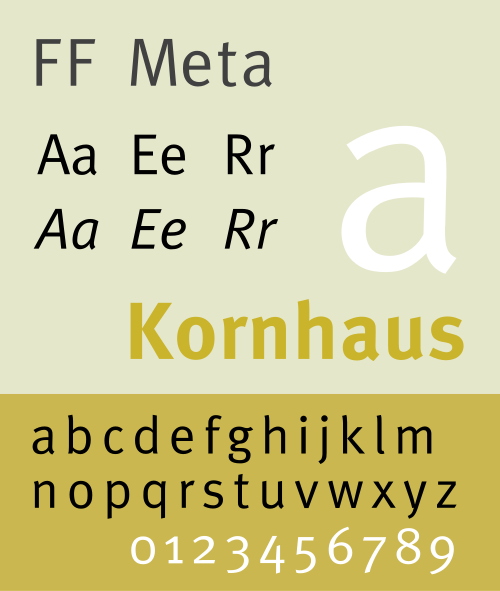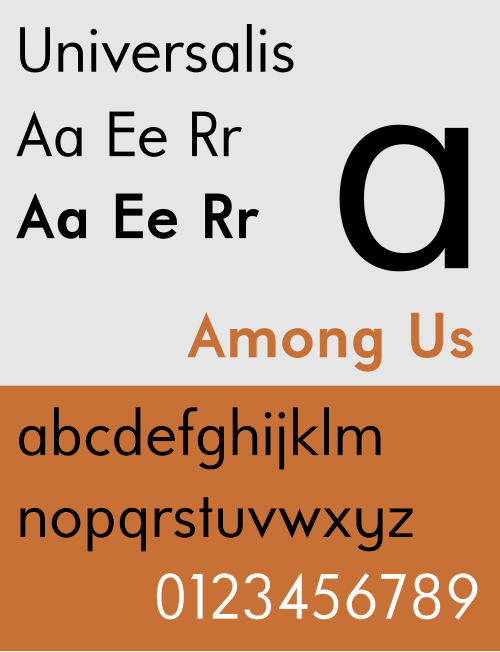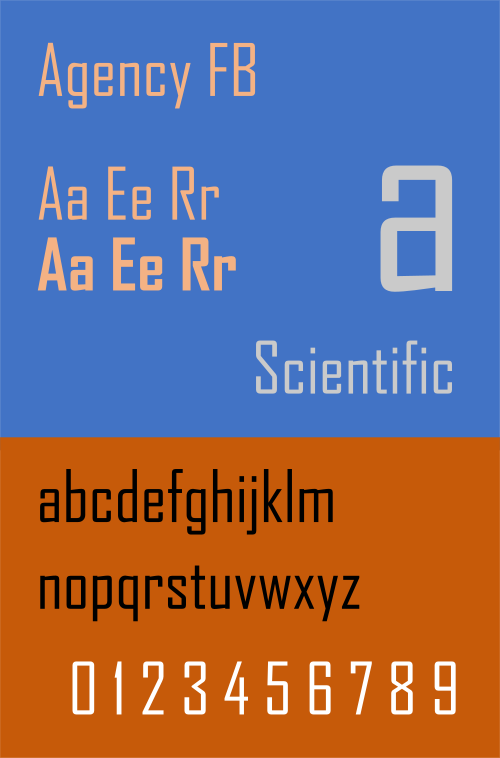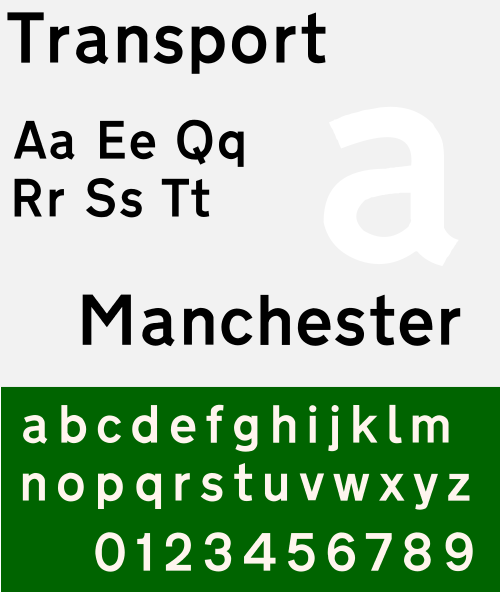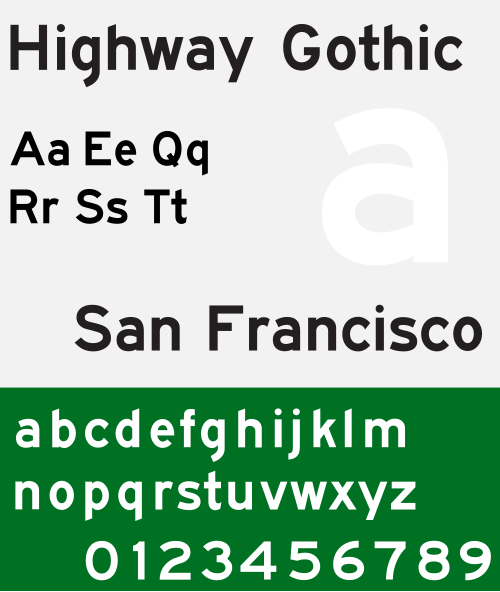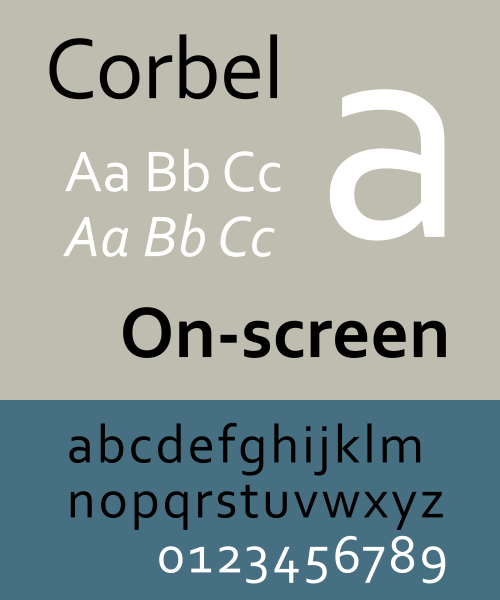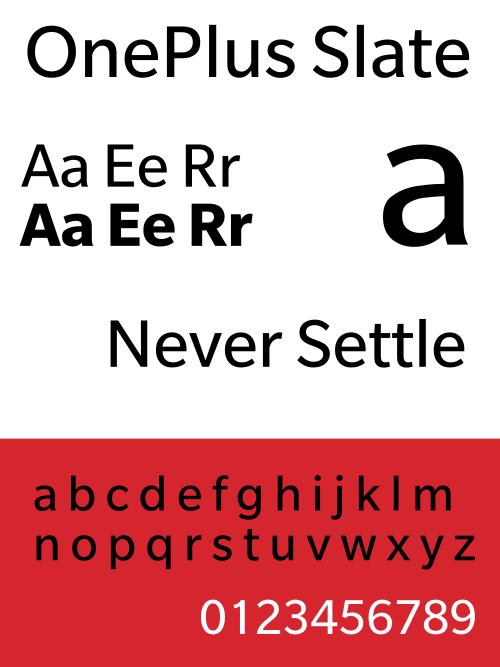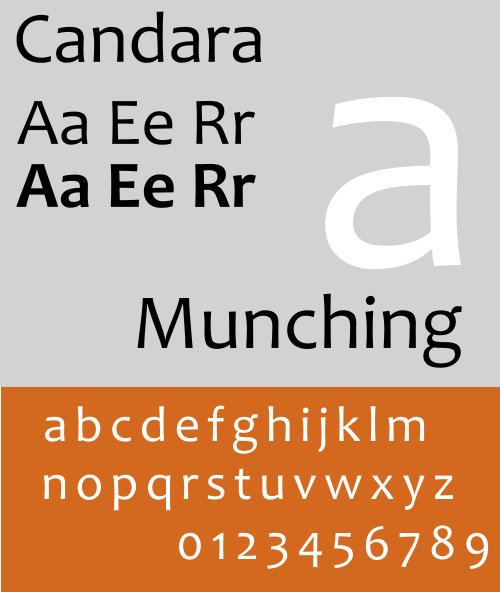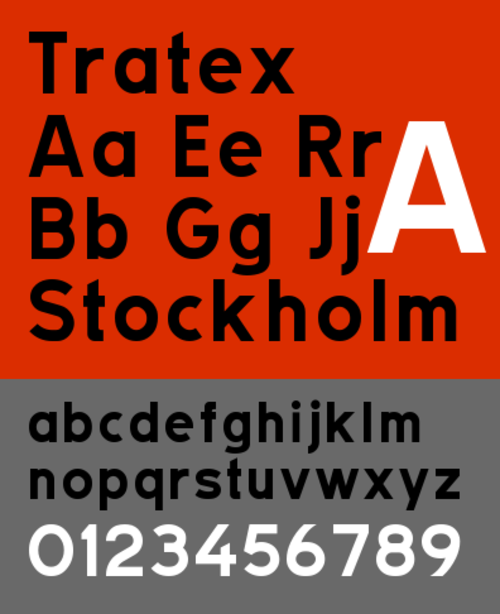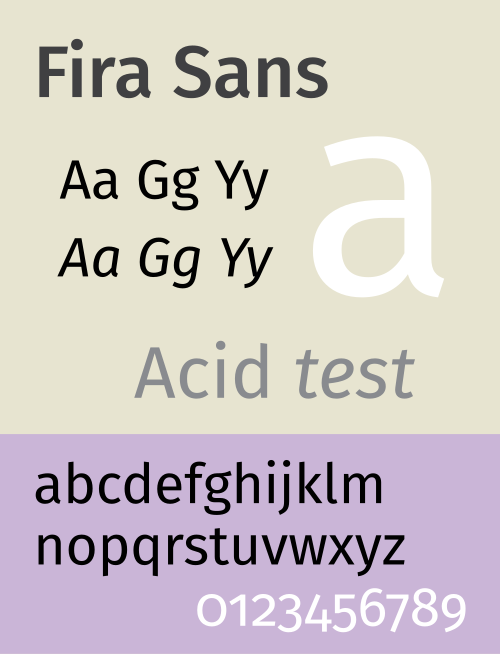
قائمة بأنواع الخطوط غير المزخرفة (sans serif)
تتضمن هذه القائمة تفاصيل عن أنواع الخطوط غير المزخرفة ( sans-serif) القياسية المستخدمة في الطباعة والتنضيد الكلاسيكي .
| مصممو وكالة فيسبوك : كالي هوبر وموريس فولر بنتون، الفئة: هندسي | |||
| Akzidenz-Grotesk المصمم: Günter Gerhard Lange الفئة: Grotesque | |||
| مصمم السعة : كريستيان شوارتز، الفئة: إنسانية | غير متوفر | |
| مصمم أندالي سانس : ستيف ماتيسون، النوع: إنساني | غير متوفر | |
| زيتون عتيق، المصمم: روجر إكسكوفون، التصنيف: إنساني | |||
| أبتوس، المصمم: ستيف ماتيسون، النوع: نيو-غروتيسك | غير متوفر | |
| مصمم الأرشيف : هيكتور جاتي، فئة النوع Omnibus: Grotesque | |||
| مصممو خط أريال : روبن نيكولاس وباتريشيا سوندرز، النوع: نيو-غروتيسك | |||
| أريمو | غير متوفر | |
| النمسا - التصنيف: هندسي | غير متوفر | |
| مصممو ITC Avant Garde Gothic : هيرب لوبالين ، توم كارناس، التصنيف: هندسي | |||
| المصمم : أدريان فروتيجر. الدرجة: هندسية | |||
| مصمم الخطوط : مايكروسوفت، الفئة: هندسي | |||
| مصمم الطراز القوطي المصرفي : موريس فولر بنتون، النوع: هندسي | |||
| مصمم احتفالات بيل المئوية : ماثيو كارتر، الفئة: إنسانية | |||
| مصمم طراز بيل غوثيك : تشونسي إتش غريفيث، النوع: غروتيسك | |||
| مصمم الطراز القوطي : إد بنغيات، التصنيف: إنساني | |||
| مصمم بوبكايجون : برايان كينت (مصمم) النوع: هندسي | |||
| مصمم خط Breeze Sans : دالتون ماج ، فئة الخط: إنساني | غير متوفر | |
| مصمم كاليبري : لوكاس دي غروت، الفئة: إنسانية | |||
| مصمم كاندارا : غاري مونش، الفئة: إنسانية | |||
| مصمم كانتاريل : ديف كروسلاند، الفئة: إنسانية | |||
| فئة الأحرف : غريبة | غير متوفر | |
| فئة العمارة القوطية في القرن التاسع عشر : هندسية | |||
| فحم ( خط نظام ماك أو إس 9 ) المصمم: ديفيد بيرلو | |||
| شيكاغو (خط نظام ما قبل نظام التشغيل Mac OS 9 ، ولا يزال مُضمّنًا في نظام التشغيل Mac OS X ) المصممة: سوزان كار | |||
| خط Adobe Clean - خط واجهة المستخدم الرسومية والأيقونات القياسي من Adobe حاليًا. النوع: إنساني، بدون نتوءات. | غير متوفر | ||
| كلير سانس (إنتل) المصمم: دان راتيجان ، جورج رايان، روبن نيكولاس | |||
| مصمم Clearview : جيمس مونتالبانو وآخرون. الفئة: إنسانية | غير متوفر | ||
| مصممو القصص المصورة الجديدة : كريج روزينسكي، هرانت بابازيان | |||
| مصمم القصص المصورة : فنسنت كوناري | |||
| مصمم كونسولاس : لوكاس دي غروت، الفئة: إنساني | |||
| مصمم الدعامات : جيريمي تانكارد، النمط: إنساني | |||
| مصمم FF Dax : هانز رايشل، الفئة: إنساني، بدون نتوءات | |||
| فئة ديجا فو سانس : إنساني | |||
| DIN 1451 المصمم: Deutsches Institut für Normung الفئة: بشع، هندسي | |||
| Drogowskaz المصمم: ماريك سيجموند الفئة: هندسي | |||
| مصمم درويد سانس : ستيف ماتيسون، الفئة: إنساني | |||
| دبي المصممة: نادين شاهين (كبيرة المصممين) الدرجة: إنسانية، شبه سبورلس | |||
| مصمم العصور : ألبرت بوتون، ألبرت هولنشتاين الدرجة: إنساني | |||
| المصمم الأوروبي : ألدو نوفاريس ، أكيرا كوباياشي الفئة: هندسية | |||
| أوكرانيا الإلكترونية المصمم: دميترو راستفورتسيف الفئة: نيو بشع | غير متوفر | |
| Fira Sans المصمم: إريك سبيكرمان ، رالف دو كاروا الدرجة: إنساني | |||
| مصمم الورقة : كونراد باور ووالتر باوم الفئة: بشع جديد | غير متوفر | |
| مصمم فرانكلين القوطي : موريس فولر بنتون، النوع: غروتيسك | |||
| فروتيجر المصمم: أدريان فروتيجر الدرجة: إنساني | |||
| FS Albert المصمم: جيسون سميث، ميتيا ميكلافتشيتش الفئة: إنساني | غير متوفر | غير متوفر |
| مصمم فوتورا : بول رينر، الفئة: هندسية | |||
| مصممة جنيف : سوزان كار، النوع: غريب الأطوار | |||
| مصمم برنامج غيرستنر : كارل غيرستنر الفئة: بشع جديد | غير متوفر | |
| مصمم خط Gill Sans : إريك جيل، الفئة: إنساني | |||
| مصمم غوثام : توبياس فرير جونز، الفئة: هندسية | |||
| مصمم اللغات العامية الكبرى : نيكولاس روبل الفئة: الخط | |||
| مصمم Gridnik : ويم كرويل، الفئة: هندسي | غير متوفر | |
| Haettenschweiler المصمم: Walter Haettenschweiler الفئة: بشع | |||
| مصممو الخط القوطي لهاندل : دون هاندل، رونالد تروجرام. النوع: هندسي، بدون نتوءات. | |||
| HarmonyOS Sans Designer: Huawei Class: Geometric | غير متوفر | ||
| مصممو خط هيلفيتيكا : ماكس ميدينجر ، إدوارد هوفمان. النوع: نيو-غروتيسك | |||
| مصمم أسلوب هاي واي جوثيك : تيد فوربس، النوع: نيو-غروتيسك | |||
| مصمم IBM Plex Sans : مايك أبينك الفئة: بشع | |||
| مصمم التأثير : جيفري لي، الفئة: غروتيسك | |||
| المصمم : راسموس أندرسون، الفئة: نيو-غروتيسك | غير متوفر | |
| مصمم الطريق السريع : توبياس فرير جونز، الفئة: مختلطة | |||
| مصمم GE Inspira : مايك أبينك الفئة: هندسية | |||
| مصمم جونستون : إدوارد جونستون ، إريك جيل. التصنيف: إنساني | |||
| مصمم كابل : رودولف كوخ، النوع: هندسي | |||
| مصمم كاريك : جان بابتيست موريزوت ، لوكاس لو بيهان الفئة: بشع | |||
| مصمم كلافيكا : إريك أولسون، التصنيف: إنساني، هندسي | غير متوفر | ||
| المصمم اللاتيني : Łukasz Dziedzic الفئة: إنساني | |||
- مشع
- دائرة حمراء
- شبكية العين
- رومولوس سانس
- روتيس سانس
- ساسون
- شيربروك
- المصدر: هان سانس
- سبارتان
- Spline Sans
- Squarish Sans CT
- SST
- مجسم
- سترودلي
- نظام
- تاس
- قالب قوطي
- الإيقاع
- الخرشنة
- تيلسون
- مترو أنفاق تورنتو
- ترافيكالفابيتيت
- ثلاثي
- القرن العشرين
- تسمية أوبونتو
- أومبرا
- URW Grotesk
- الزهرة
- زيورخ